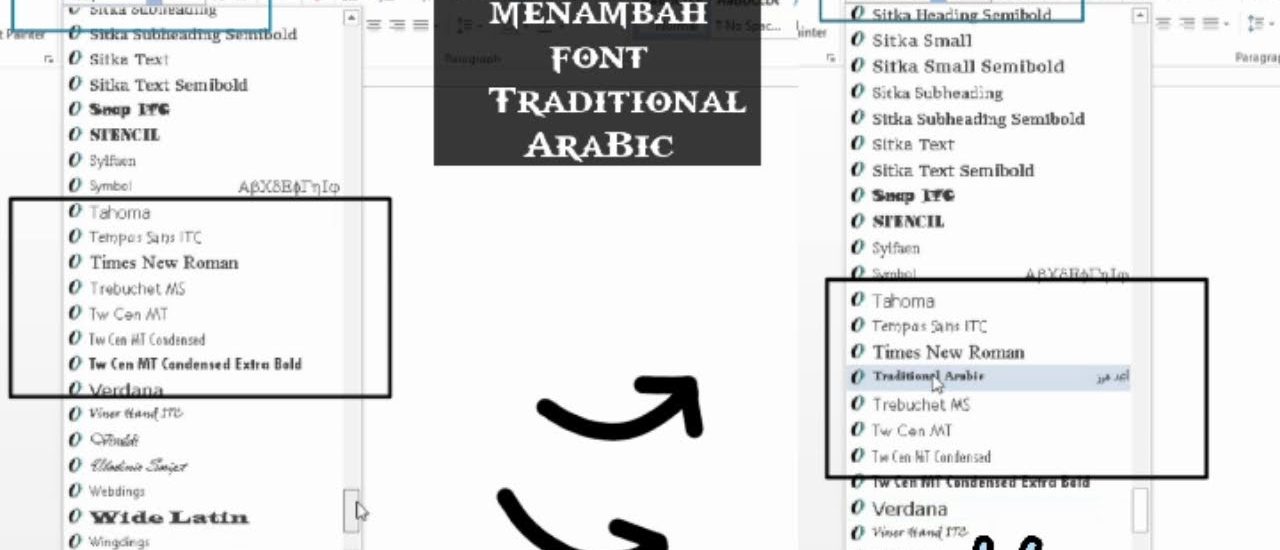
Masalah font arab berubah di word seringkali membuat dokumen menjadi tidak rapi dan sulit dibaca. Perubahan ini biasanya terjadi saat file dibuka di perangkat lain atau setelah proses penyalinan teks. Artikel ini akan membahas penyebab umum dan memberikan solusi praktis agar tulisan Arab tetap konsisten.
Mengapa Font Arab Sering Berubah Secara Otomatis?
Perubahan font sering dipicu oleh pengaturan default Word yang mengganti jenis huruf sesuai dengan bahasa yang terdeteksi. Sistem operasi juga memiliki font fallback yang digunakan ketika font asli tidak tersedia di perangkat. Selain itu, penggunaan font arab di word yang tidak kompatibel antar versi dapat memicu perubahan tampilan.
Faktor lain adalah ketika Anda menyalin teks dari sumber eksternal seperti PDF atau situs web, format font asli ikut terbawa. Word kemudian mencoba menyesuaikan dengan font standar yang ada di pengaturan dokumen. Memahami penyebab ini adalah langkah awal untuk mencegah masalah serupa di masa depan.
Cara Mengatasi Font Arab Berubah di Word
1. Atur Font Default untuk Bahasa Arab
Anda bisa mengatur font default khusus untuk teks Arab melalui menu ‘Font’ di Word. Pilih tab ‘Advanced’ dan atur ‘Font’ untuk ‘Complex Scripts’ sesuai keinginan. Dengan begitu, setiap pengetikan huruf Arab akan otomatis menggunakan font yang dipilih.
Pastikan juga untuk mengubah pengaturan ‘Set As Default’ agar berlaku untuk semua dokumen baru. Cara ini efektif untuk mencegah font arab berubah di word saat memulai dokumen baru. Jangan lupa untuk menyimpan perubahan dengan memilih opsi ‘All documents based on the Normal template’.
2. Gunakan Fitur ‘Paste Special’ untuk Menjaga Format
Ketika menyalin teks Arab dari sumber lain, gunakan opsi ‘Keep Text Only’ atau ‘Merge Formatting’. Fitur ini akan menghapus format asli dan menyesuaikan dengan font yang sedang aktif. Ini adalah solusi cepat untuk menghindari perubahan font yang tidak diinginkan.
Jika Anda sering menyalin teks dari web, pertimbangkan untuk menggunakan ‘Paste Special’ dan pilih ‘Unformatted Text’. Cara ini memastikan teks Arab mengikuti pengaturan font default yang sudah Anda atur. Dengan demikian, konsistensi tampilan dokumen tetap terjaga.
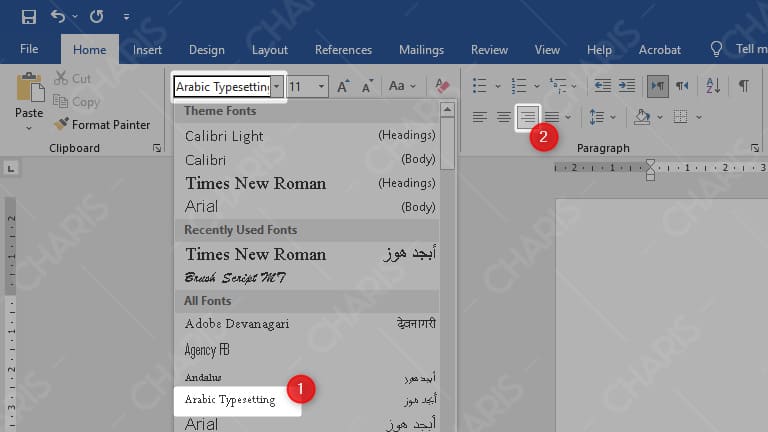
3. Periksa Ketersediaan Font di Perangkat Lain
Masalah font arab berubah di word sering terjadi karena font yang digunakan tidak terpasang di komputer lain. Jika dokumen akan dibagikan, gunakan font yang umum seperti Traditional Arabic atau Simplified Arabic. Anda juga bisa mengonversi dokumen ke PDF agar font tidak berubah.
Alternatif lain adalah dengan menyematkan font ke dalam file Word melalui menu ‘File’ > ‘Options’ > ‘Save’. Centang opsi ‘Embed fonts in the file’ untuk memastikan font tetap utuh. Namun, perlu diingat bahwa ukuran file akan menjadi lebih besar.
Rekomendasi Font Arab Terbaik untuk Word di Tahun 2026
Memilih font yang tepat sangat penting untuk kenyamanan membaca dan estetika dokumen. Berikut adalah beberapa font arab terbaik yang direkomendasikan untuk berbagai kebutuhan, baik untuk dokumen formal maupun kreatif.
- Traditional Arabic – Font klasik yang paling stabil dan kompatibel dengan semua versi Word. Cocok untuk dokumen resmi dan naskah akademik.
- Simplified Arabic – Tampilannya lebih modern dan bersih, sangat baik untuk teks panjang karena keterbacaannya tinggi.
- Arabic Typesetting – Font yang dirancang khusus untuk keperluan percetakan dan desain, dengan bentuk huruf yang proporsional.
- Omar Regular – Font bergaya kaligrafi yang elegan, cocok untuk judul atau kutipan agar terlihat artistik.
- Amiri – Font open-source yang populer untuk teks Al-Quran dan literatur Islam, tersedia gratis dan mudah diunduh.
Tips Memilih Font Arabic yang Tepat
Untuk dokumen yang bersifat formal, seperti surat resmi atau laporan, pilihlah font arab serif seperti Traditional Arabic. Sedangkan untuk presentasi atau materi digital, font arab modern seperti Simplified Arabic lebih disarankan. Pastikan juga font tersebut mendukung harakat (tanda baca) jika diperlukan.
Jika Anda membutuhkan gaya tulisan tangan, font arab handwriting dapat memberikan kesan personal dan hangat. Namun, hindari penggunaan font yang terlalu rumit untuk teks isi yang panjang karena dapat mengurangi kenyamanan membaca. Uji coba beberapa font sebelum menentukan pilihan akhir.
Kesimpulan
Masalah font arab berubah di word dapat diatasi dengan pengaturan font default yang tepat dan penggunaan fitur paste yang benar. Pastikan selalu memilih font yang kompatibel dan tersedia di perangkat lain untuk menghindari perubahan yang tidak diinginkan. Dengan mengikuti panduan di atas, dokumen Arab Anda akan tampil konsisten dan profesional.